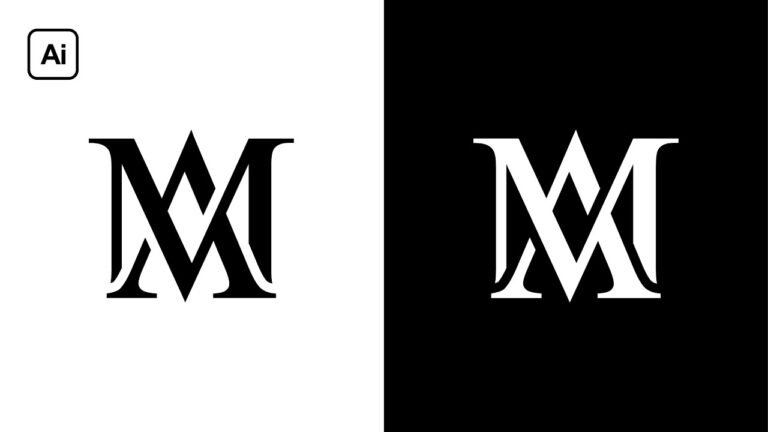
Diseño de logotipos con tipografía moderna: claves para el éxito
En el mundo del diseño gráfico, la creación de logotipos con tipografía moderna se ha convertido en una tendencia cada vez más popular. La combinación de fuentes contemporáneas y estilos innovadores permite a las marcas destacar y transmitir su identidad de una manera única y atractiva. En este artículo, exploraremos la importancia de la tipografía en la creación de logotipos y cómo las empresas pueden aprovechar esta técnica para lograr un impacto visual poderoso en sus audiencias.
¿Qué tipografía usar para un logotipo?
A la hora de elegir la tipografía para un logotipo, es importante evitar aquellas que son muy comunes en textos y documentos, como Arial. En su lugar, es recomendable optar por fuentes clásicas y sencillas, como Helvética, Roboto, Soho, Din o Futura. Estas tipografías suelen funcionar mejor para logotipos, ya que son más distintivas y tienen un impacto visual más fuerte.
La elección de la tipografía para un logotipo es crucial para la imagen y la identidad de una marca. Es por ello que es fundamental seleccionar fuentes que sean distintivas y que reflejen la personalidad de la marca. Optar por tipografías clásicas y sencillas, como Helvética, Roboto, Soho, Din o Futura, puede ayudar a crear un logotipo que sea fácilmente reconocible y memorizable para el público.
En resumen, al elegir la tipografía para un logotipo, es importante evitar las fuentes comunes y optar por aquellas que sean más distintivas y representativas de la marca. Tipografías clásicas y sencillas, como Helvética, Roboto, Soho, Din o Futura, suelen funcionar mejor para logotipos, ya que tienen un impacto visual más fuerte y contribuyen a la identidad de la marca.
¿Cuál es la transmisión de la tipografía moderna?
Las serifas modernas tienen un diseño limpio y minimalista, lo que las hace perfectas para comunicar un mensaje de sofisticación y modernidad. Su estilo elegante y pulido las convierte en una elección popular para proyectos que buscan transmitir confianza y profesionalismo.
El Impacto del Estilo y Concepto en el Diseño de Logotipos
Además, la tipografía moderna con serifas puede añadir un toque de jerarquía y estructura a un diseño, ayudando a guiar al lector a través del contenido de manera clara y organizada. Su presencia sutil pero impactante puede mejorar la legibilidad y la cohesión visual de un texto, lo que la convierte en una opción versátil para una amplia gama de aplicaciones creativas.
¿Cuál es el tipo de letra más elegante?
La tipografía más elegante es la llamada "Bodoni". Su diseño refinado y sus líneas finas la hacen perfecta para proyectos que requieren un toque de sofisticación y estilo. La elegancia de la tipografía Bodoni radica en su equilibrio entre la simplicidad y la elegancia, lo que la convierte en una elección popular para logotipos, invitaciones y material impreso de alta gama.
Otro tipo de letra que destaca por su elegancia es la "Garamond". Esta tipografía clásica se caracteriza por sus formas delicadas y su legibilidad excepcional, lo que la convierte en una opción ideal para textos largos en publicaciones editoriales y documentos formales. La Garamond es una elección segura si buscas transmitir sofisticación y refinamiento en tus diseños de comunicación.
Elementos clave para un diseño de logotipo impactante
Un diseño de logotipo impactante debe ser único, memorable y relevante para la marca que representa. Cada elemento, desde el color hasta la tipografía, debe ser cuidadosamente seleccionado para transmitir la identidad y los valores de la empresa. La simplicidad es clave en un logotipo efectivo, ya que facilita su reconocimiento y memorabilidad. Un buen diseño de logotipo debe ser versátil y funcionar bien en diferentes tamaños y medios, asegurando que la marca se destaque en cualquier contexto.
Cómo elegir la tipografía perfecta para tu logotipo
A la hora de elegir la tipografía ideal para tu logotipo, es importante considerar la personalidad de tu marca. La tipografía comunica tanto como los colores y el diseño, por lo que debe reflejar la esencia de tu negocio. Si buscas transmitir profesionalidad y confianza, opta por fuentes serif. En cambio, si deseas proyectar modernidad y creatividad, las fuentes sans-serif son una excelente elección.
Revolución en el Diseño de Logotipos: Innovación y Creatividad
Además de la personalidad de tu marca, es fundamental tener en cuenta la legibilidad de la tipografía. Un logotipo debe ser fácil de leer en cualquier tamaño y en diversos medios. Evita fuentes muy ornamentadas o con demasiados detalles, ya que pueden dificultar la lectura. Opta por tipografías limpias y legibles que se adapten a diferentes contextos sin perder su impacto visual.
Por último, no te olvides de la coherencia entre la tipografía de tu logotipo y el resto de la identidad visual de tu marca. Mantén una paleta de fuentes consistente en todos tus materiales de marketing para reforzar la imagen corporativa. La elección de la tipografía perfecta para tu logotipo es un paso crucial en la construcción de una marca sólida y memorable.